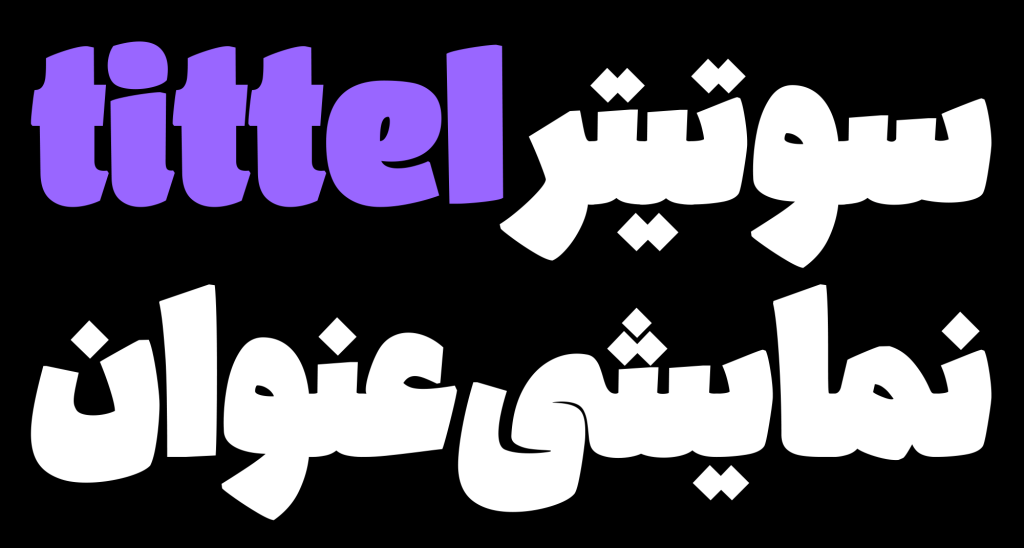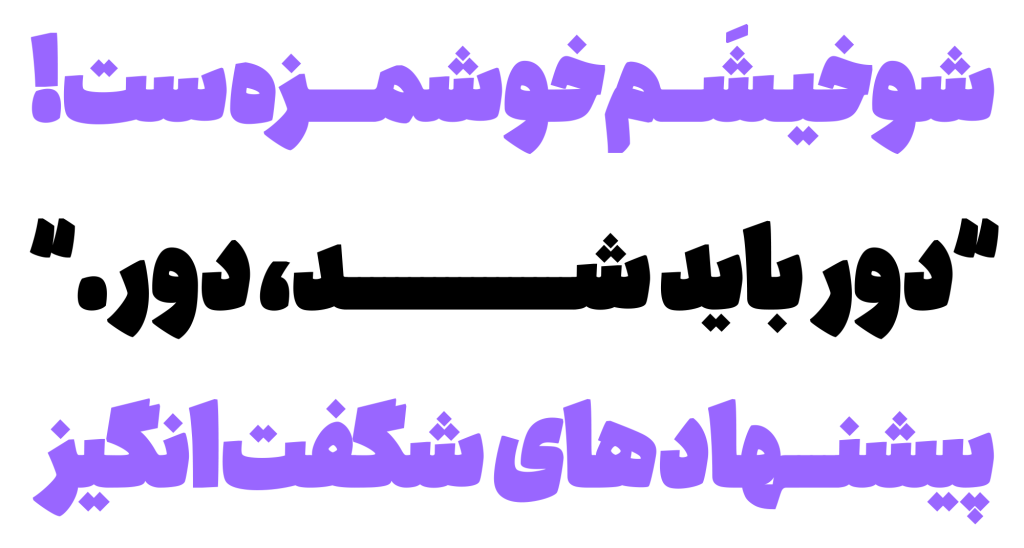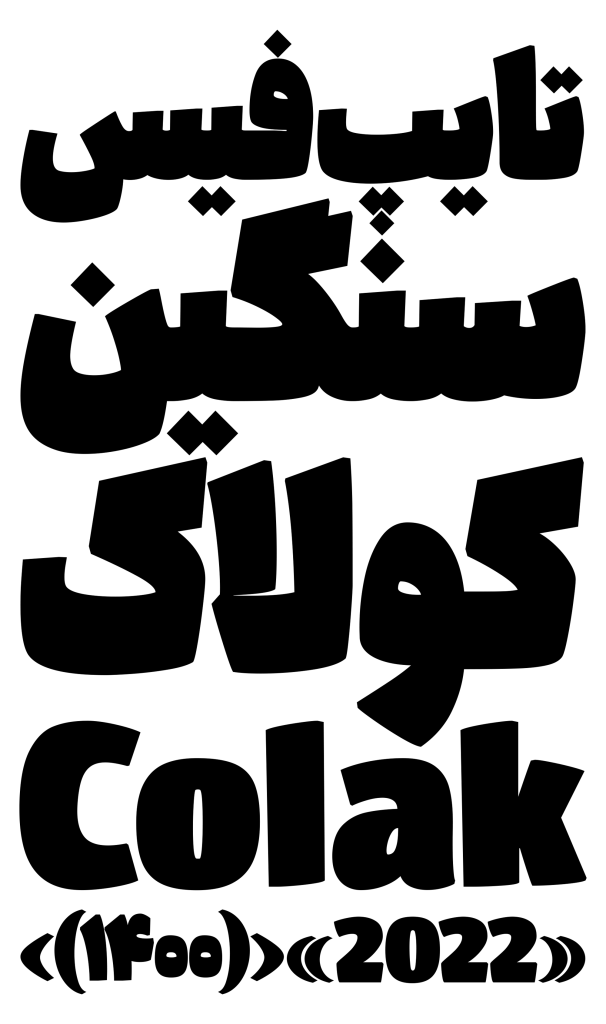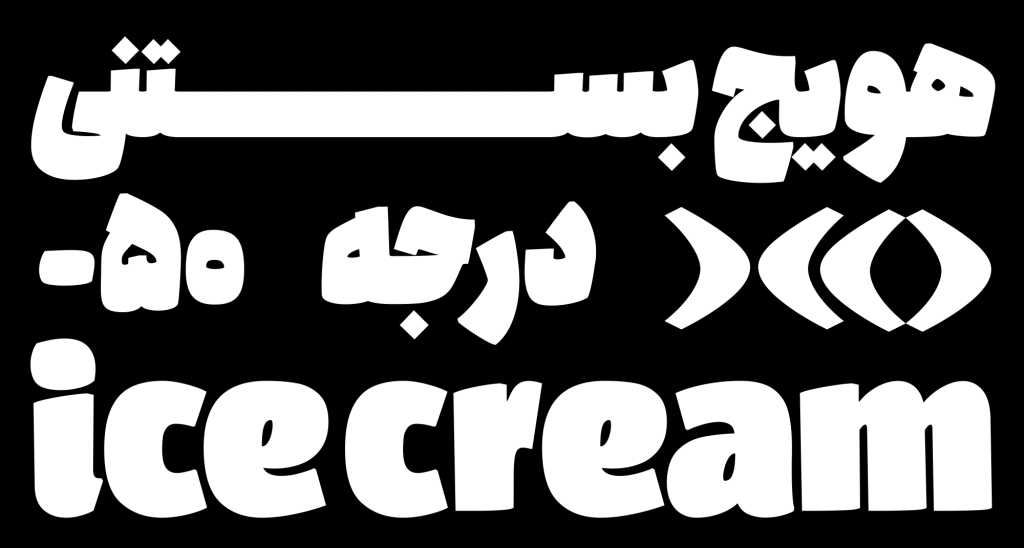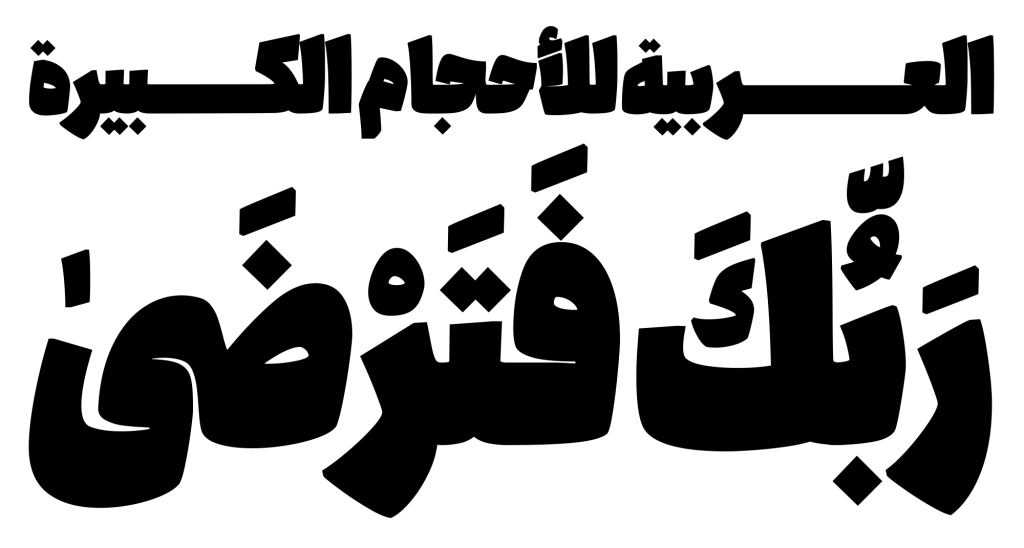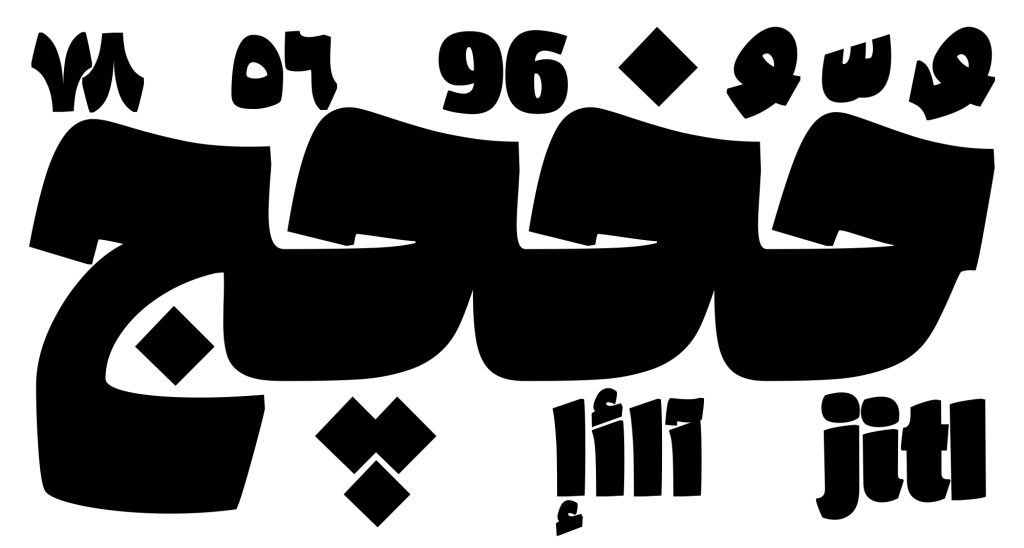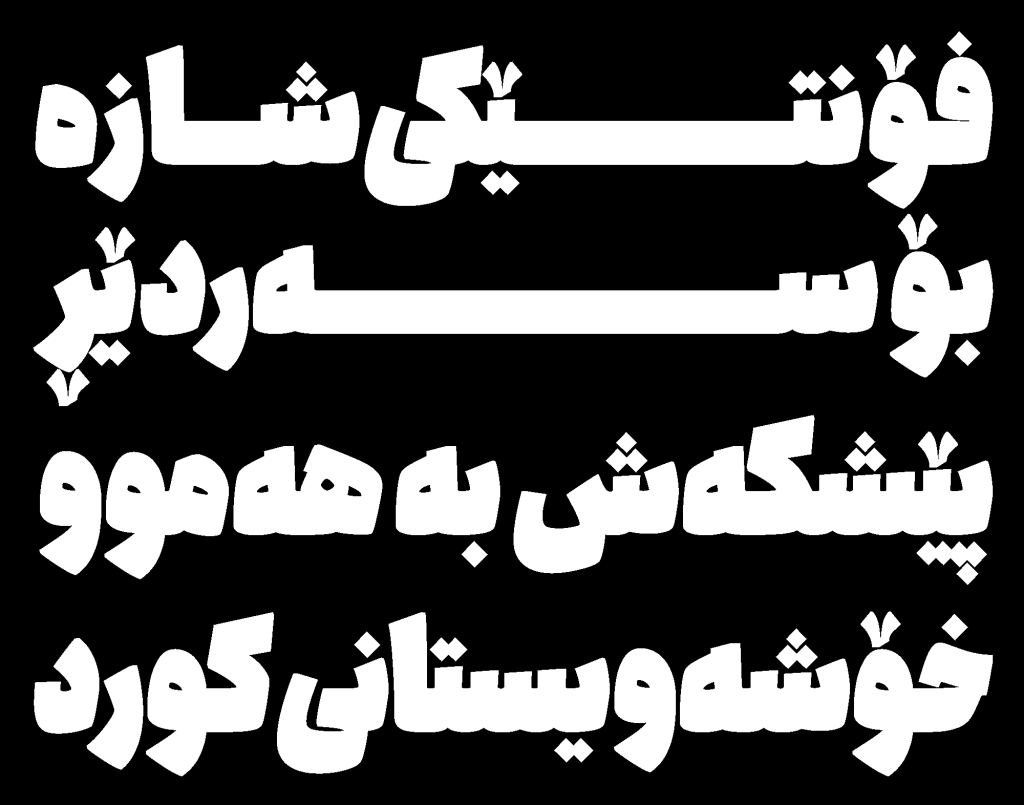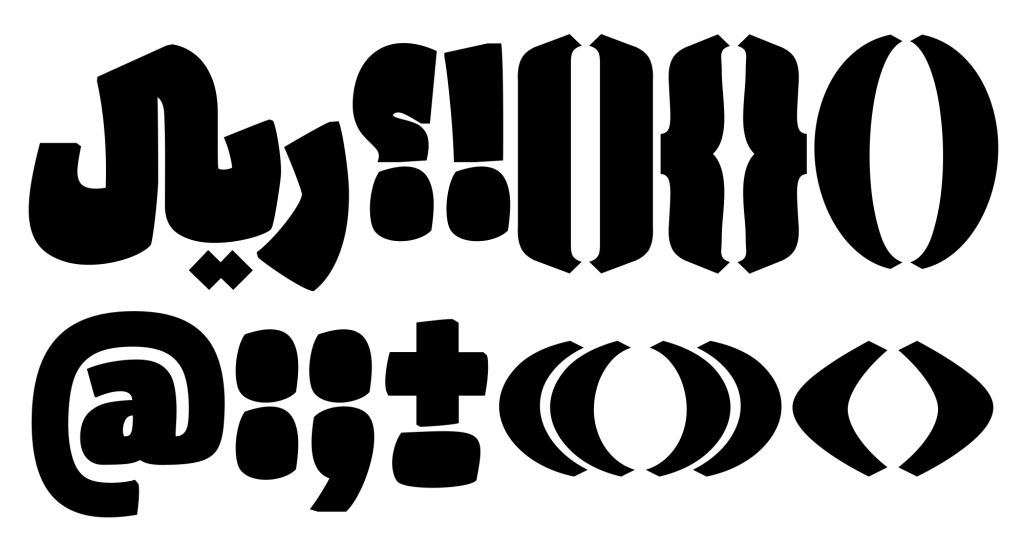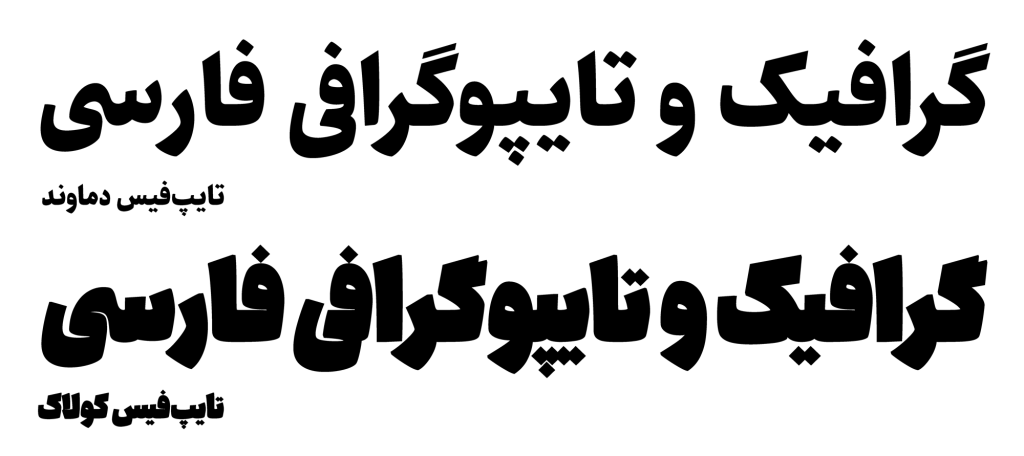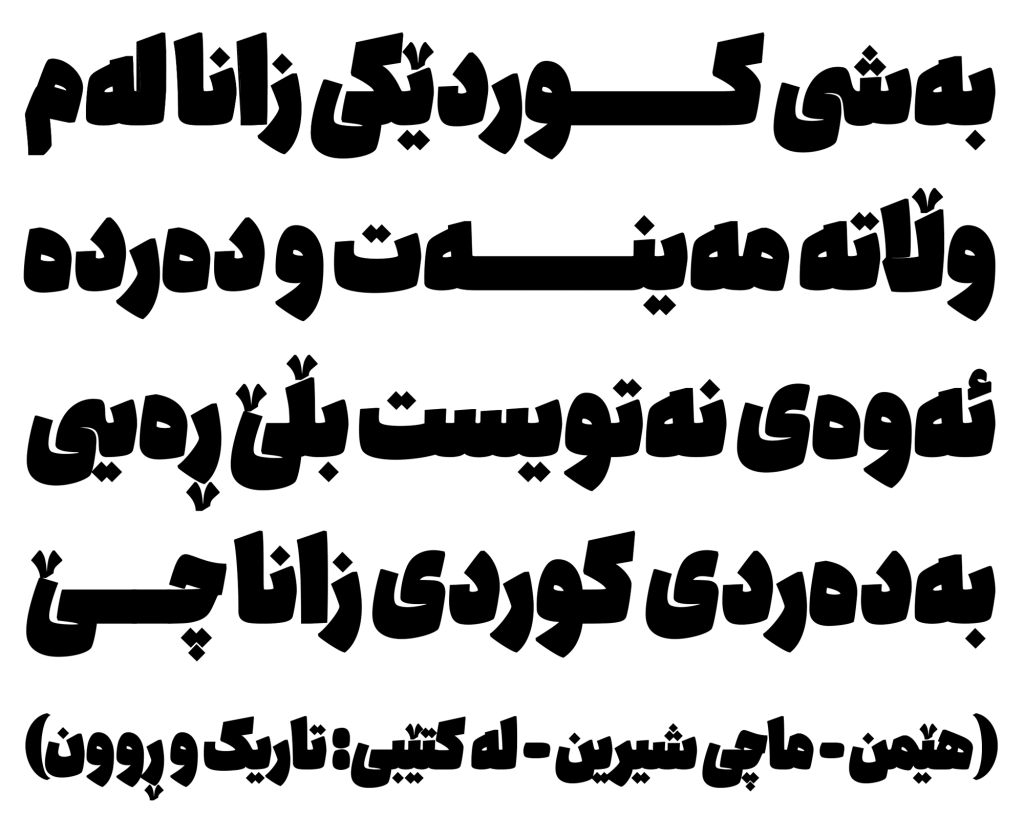
فونت کولاک قلمی تبلیغاتی برای شما
فونت کولاک قلمی با طراحی امیر مصباحی خلق و ایجاد گردید اگر به دنبال جذب مخاطبان خود با عناوین و متون کوتاه هستید بی شک این قلم انتخابی بسیار مناسب برای شما عزیزان خواهد بود . در رده این دسته از تایپ فیس های با چنین ضخامت در سطح و کنتراست می توان به فونت ونوو اشاره نمود که همانند این قلم از خانواده نسخ می باشد.
کولاک در تعریف لغت به حالت یا هنگامی گفته می شود که تداخل و برهم کنشی بین دو سیستم پرفشار و کم فشار ایجاد شود .در این زمان کولاکها شکل میگیرند، . ایده اولیه طراحی این قلم در زمستان در یکی از سردترین شهرهای ایران در این فصل یعنی همدان شکل گرفت گویا همین فضای برهم کنشی ایده را به طراح این قلم متبادر کرده تا این تایپ فیس شکل گیرد. «مقابله فضای سنگین مثبت با حداقل فضای منفی در یک سطح» سرانجام این امر در بهمن 99 شکل گیری و دیزاین آن نیز در تابستان و پاییز ۱۴۰۰ به سرانجام رسید.
تمرکز طراح بر حفظ روحیه رسمی و اجتناب از اغراق و ایجاد محدودیت فضای های منفی در بین کاراکترها بوده است، تا کاربران این فونت بتوانند فضای تایپوگرافی و گرافیک متفاوتری را حس و تجربه نمایند. کولاک در عین حفظ اقتضائات و فضای رسمی خود دارای شخصیت نمایشی و جذاب نیز می باشد.
پشتیبانی کولاک از زبان های مختلف
شایان ذکر است که قلم کولاک در پشتیبانی از زبان های مختلف حرف برای گفتن داره این قلم زیبا
توجه خاصی به زبان کوردی هم دارد و همچنین از زبان عربی نیز پشتیبانی میکند و جهت هماهنگی و نمایش بهتر کلمات لاتین، حروف خط لاتین نیز برای زبان انگلیسی طراحی شده است.